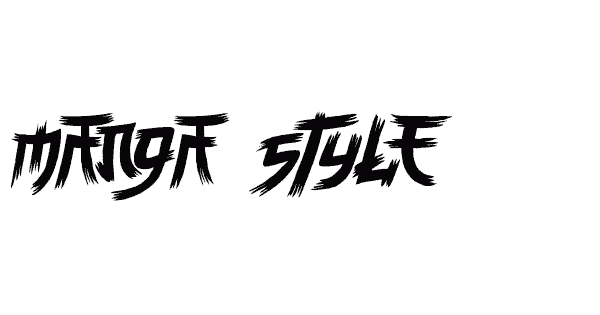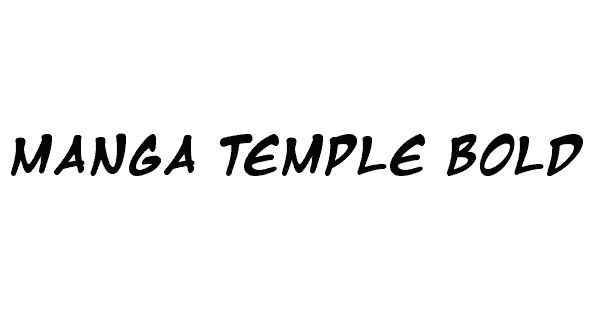
Шрифт в русской манге
Каким бы ты небыл гуру-тайпером, но если шрифт подобран плохо — вся работа будет выглядеть плохо. Как правило в русском сканлейте для этих целей служить Anime Ace. Сканлейт, Перевод, Манга.
Сборник русских шрифтов в японском стиле. Всего в папке одиннадцать шрифтов с буквами, по начертанию похожими на иероглифы. Поддерживается как кириллица, так и символы латинского алфавита. Просто распакуйте архив и установите необходимые вам шрифты в
Русские шрифты в японском стиле
Красивые шрифты для манги
Русские шрифты, с поддержкой кириллицы. Скачать красивые шрифты бесплатно на Fontsup.Обычно должен быть больше обычного шрифта на 1-3 пункта. Применение: используется для восклицаний, облака не овальные, с резкими или обрывистыми границами. Если он используется также для мыслей персонажа, то рекомендую для этого случая размер равный обычному
Делать всё одинаковым шрифтом — это не хорошо, мы не переводим мангу, которую нужно выкладывать почти сразу же, после её
- Мир шрифтов велик и многогранен! В нём полно всякого разного: у многих шрифтов разные цели и применения, которые определяют их использование и делят их на своего рода категории.
Список шрифтов для тайпсета 2.0 — Русское сканлейт-общество
Шрифты для передачи речи: • Итак, поговорим о шрифтах, которые используют для передачи речи в облачках.
Статистика и гигабайты прочитанной манги показываются, что чаще всего тайпсеттеры используют шрифт AnimeAce V02, чуть реже – Manga Temple и IrinaCTT.
Шрифты для манги с кириллицей